50 ejemplos de composiciones con tipografía de estilo "vintage"
Dicen que las modas siempre vuelven y el estilo "
vintage" es la demostración práctica más evidente de esa máxima, ya que retoma los diseños de hace algunas décadas y se inspira en ellos para crear composiciones nuevas. Esta tendencia se mira en el espejo de los
años 50, 60 y 70, pero también en los ejemplos surgidos a
comienzos del siglo XX. Así pues, para definir los productos que conformarían esta clase de ambientes hay que hacer una especie de viaje en el tiempo.
¿Qué es
vintage? Se le llama "
vintage" a todo aquello que ha pasado de moda que hoy se considera clásico. Se aplica el adjetivo "
vintage" especialmente a aquello considerado de gran calidad. La palabra "
vintage", en una primera acepción en idioma inglés, significa "
vendimia". Está relacionada con la cosecha de uva y la producción de vino. El término se extendió para usarlo en todo aquello con origen definido y calidad sobresaliente.
Por lo tanto
vintage es precisamente ese objeto original al que el estilo retro pretende emular.
Según comentan en el artículo
50 Examples of Vintage Typography, de
WebDesignerDepot, el arte
vintage nos recuerda un momento en el que se depende menos de la tecnología y más en la habilidad y la técnica.
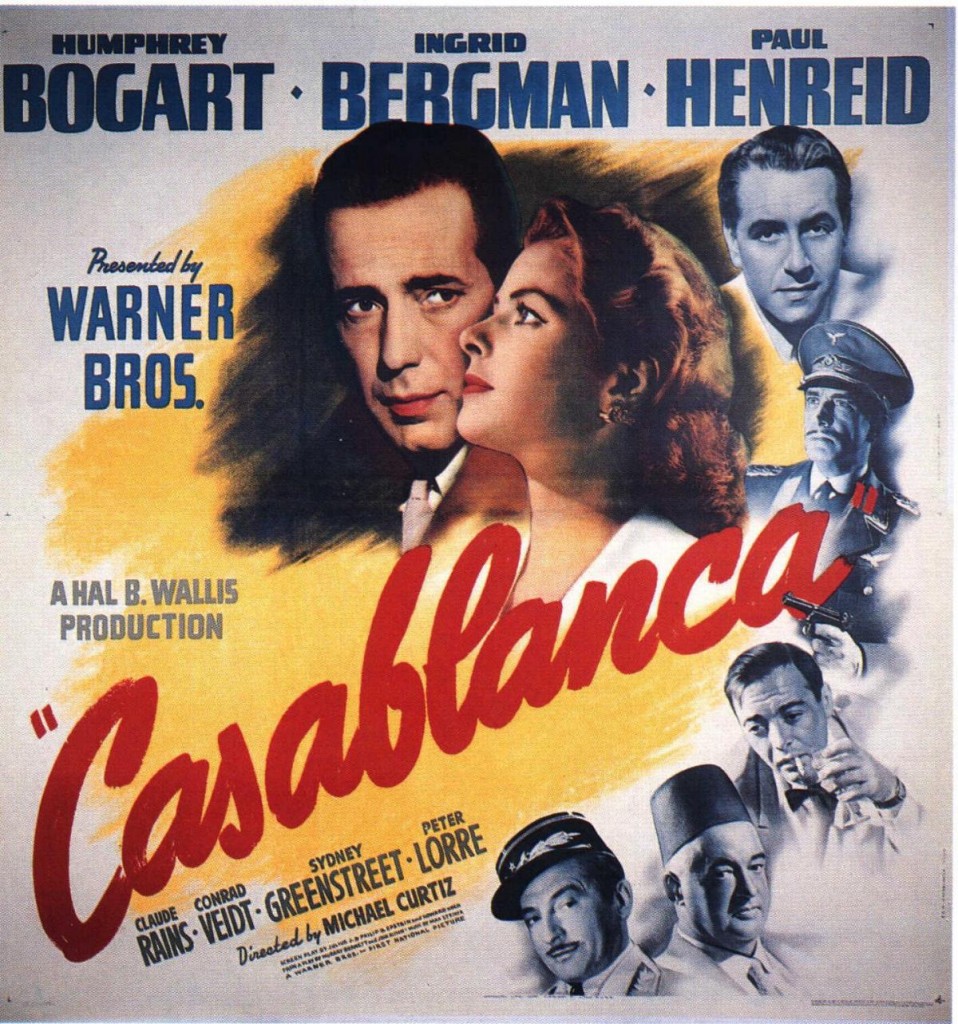
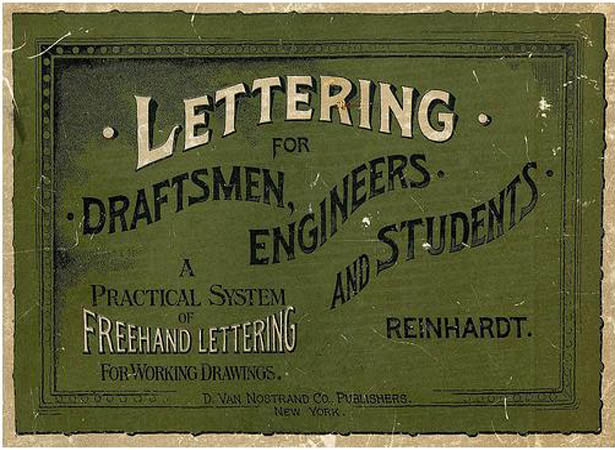
Como dicho artículo nos habla de 50 jemplos de tipografías con estilo
vintage, encontrarás un buen puñado de ejemplos tipográficos que muestran una amplia gama de estilos artísticos de los últimos 100 años. No podemos comparar la tipografía de hace 100 años a la de hoy, con la llegada de tantos nuevos tipos de letra, crear nuevas formas de tipos de letras, así como nuevas formas de obtener nuestra obra de arte en el mundo.
A pesar de que la aplicación de la tipografía ha evolucionado mucho desde hace un siglo hasta ahora, el más común el uso de la tipografía sigue siendo para los anuncios, señales y logotipos.